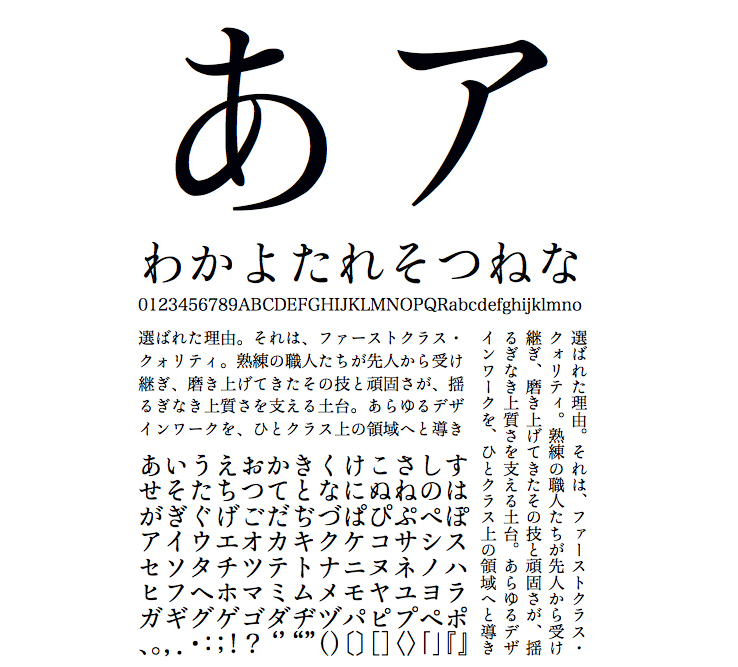
仮名・英数字グリフのみ収容
※本商品は仮名書体です。ギャラリーの見本に含まれる漢字はヒラギノ明朝を使用しています。
【游築(ゆうつき)五号仮名】明治後期に作られた東京築地活版製造所の五号明朝体活字をもとに、「ヒラギノ明朝」に合わせるため元の書体の字面の大きさや太さの調整を行い、やや現代風にデザインしたオリジナルの仮名書体です。「ヒラギノ明朝体」の漢字と組み合わせて使用できるようにデザインしています。
游築五号仮名 W3